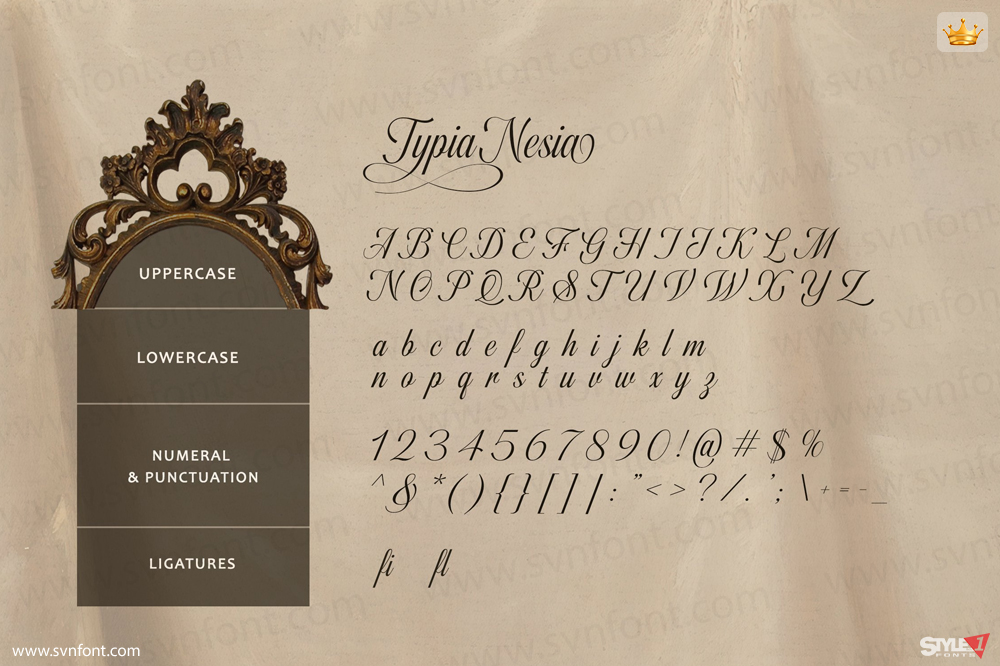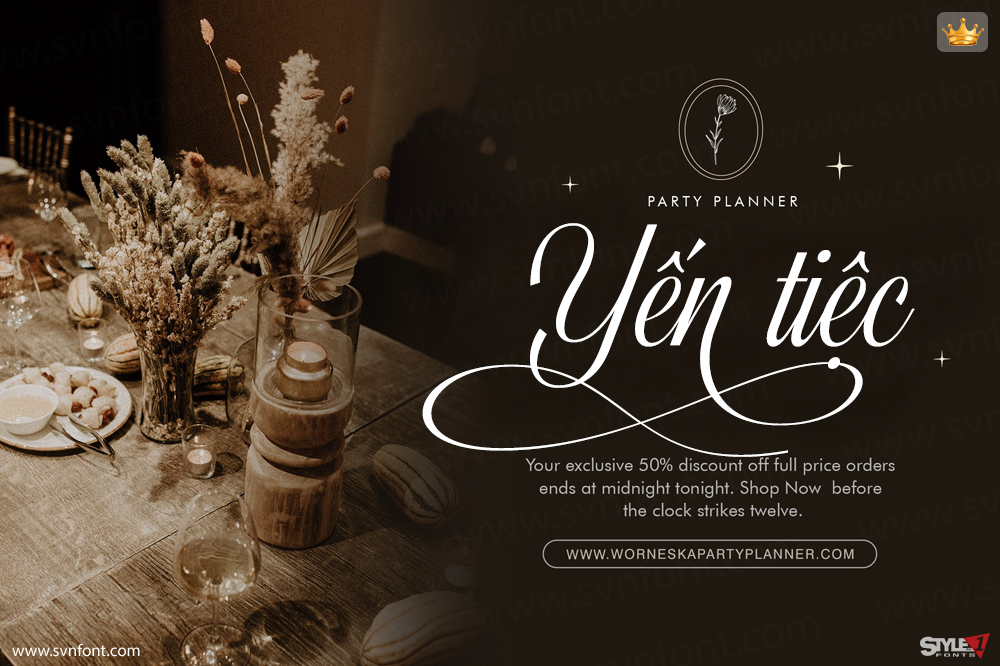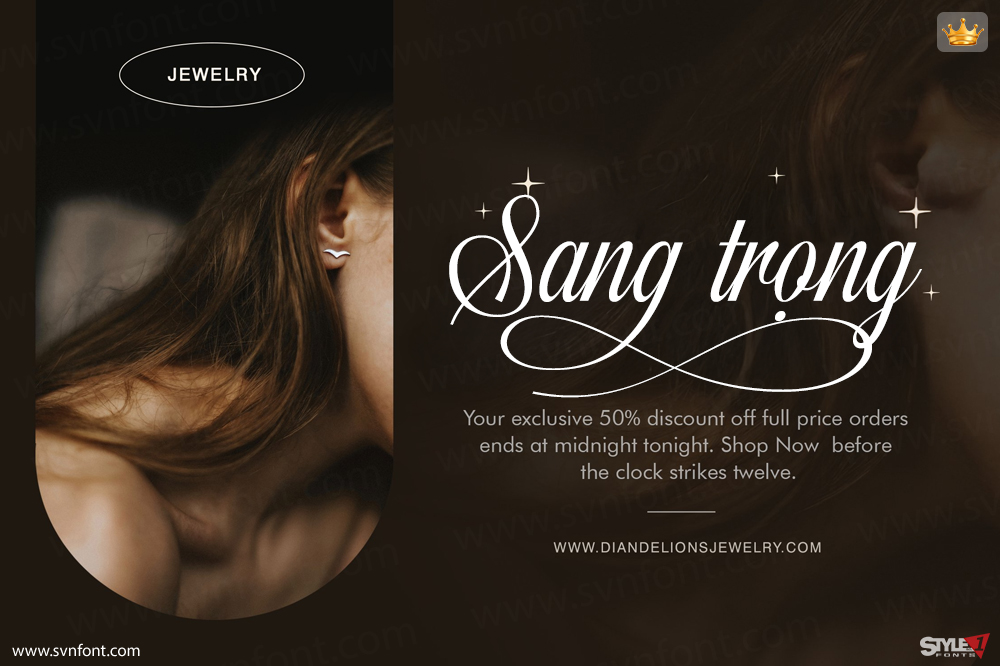
Fairyfiesta – Phông Chữ Script Cổ Điển Thanh Lịch – Phông Chữ Hoàng Gia Sang Trọng Cổ Điển Tuyệt Đẹp
Phông chữ Fairyfiesta đi kèm với các biến thể glyph như Chữ Ghép, Chữ Thay Thế và Nét Uốn Cong. Bạn có thể kết hợp chúng để tạo ra một thiết kế typography hoàn hảo. Nó rất phù hợp cho các dự án sắp tới của bạn. Chẳng hạn như logo và xây dựng thương hiệu sang trọng, thiết kế biên tập đẳng cấp, tạp chí phụ nữ, thương hiệu mỹ phẩm, quảng cáo thời trang, xây dựng thương hiệu phòng trưng bày nghệ thuật, bảo tàng, lịch sử kiến trúc, xây dựng thương hiệu cửa hàng, thiết kế văn phòng phẩm, thiết kế blog, thiết kế quảng cáo hiện đại, thiệp mời, trích dẫn nghệ thuật, trang trí nhà cửa, tiêu đề sách/bìa sách, các sự kiện đặc biệt và nhiều hơn nữa.
Nhà thiết kế: Typia Nesia
Nhà phát hành: Typia Nesia